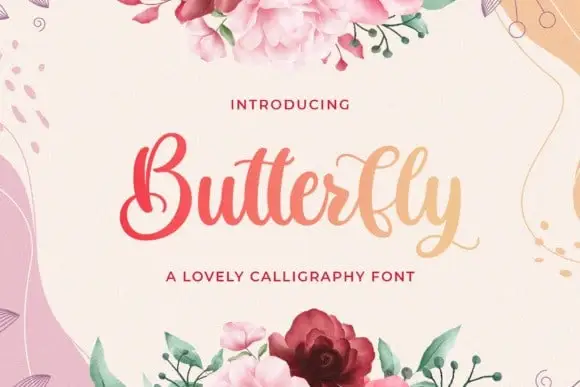
Introduzimos a Butterfly Calligraphy Font — uma tipoografia encantadora e leve que traz uma variedade de alternativas, ligaturas e terminações com swashes. Este font é perfeito para qualquer projeto onde você deseja adicionar um toque autêntico e delicado à sua arte. Com seu designer, StringLabs, esse tipo é tão encantador quanto elegante. Ideal para os detalhes finos de cartões de agradecimento, convites de casamento, cartazes de boas-vindas, logotipos, cartões de negócios e qualquer outro projeto que precise de uma pitada de escrita à mão. Além disso, graças à sua codificação PUA, você pode acessar todas as linhas e swashes com facilidade. Com seu desvio do nível base e traços suaves, Butterfly Calligraphy Font tem ganchos hermosos e alternativas que deixam seu design ainda mais atraente. Esta font é perfeita para aqueles que buscam um toque delicado em seus projetos de design, sem ter que recorrer à escrita manuscrita exata.